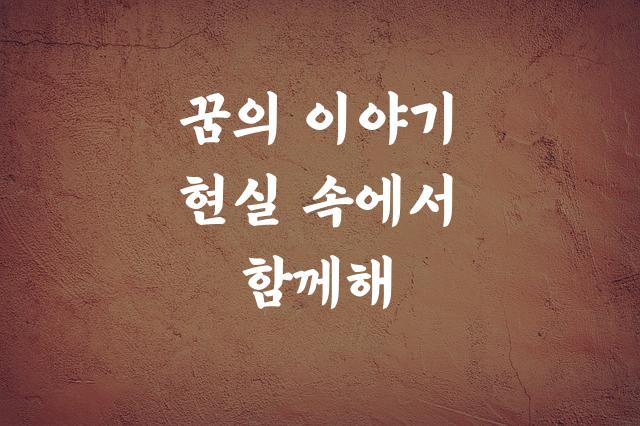
만세체는 윤디자인M에서 제작한 붓글씨 스타일의 캘리그라피 폰트입니다. 고전적 감성을 현대적인 디자인으로 재해석하여, 우아하고 섬세한 느낌을 전달합니다.
만세체은(는)
손글씨, 명조/전통, 펜/붓터치, 감성적인, 복고풍 계열의 생김새를 가지고 있으며
포스터, 광고 캠페인, 소셜 미디어 등에서 자주 활용되며, 효과적인 메시지 전달에 적합합니다.
이 폰트는 크리에이티브, 문화/예술, 엔터테인먼트 분야에 잘 어울리며,
친근한, 창의적인, 재미있는 느낌을 담고 있는 것이 특징입니다.